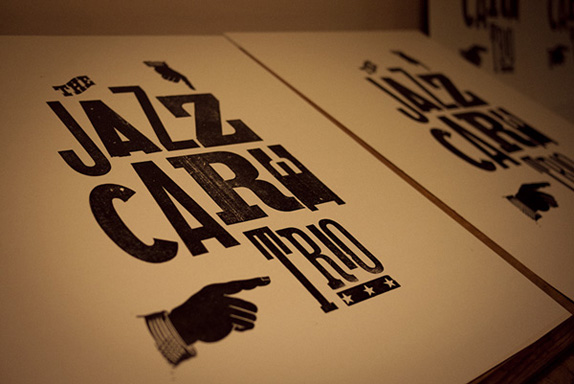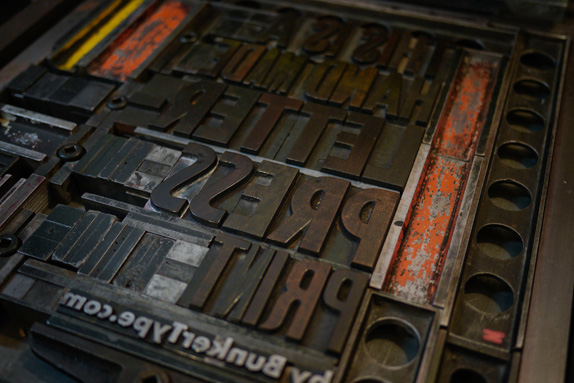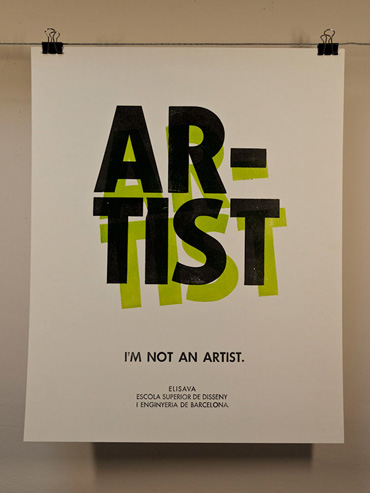
Hoy las computadoras nos ofrecen una suerte de depósitos virtuales en los que almacenamos gran cantidad de material sin ocupar espacio físico, y nos ofrece facilidad para acceder individualmente a cada uno de los archivos.En Bunker Type la realidad es diferente… Rodeado de Prensas, interlineas, filetes, tintas, y una gran colección de tipos móviles (150 familias de plomo en cuerpos relativamente grandes y 50 en madera) Jesús genera piezas gráficas artesanales colmadas de elegancia y sensibilidad.
«Voy recopilando de poco en poco… ¡pero sin pausa! Luego la mayoría de material no lo llego a usar… simplemente está ahí por si se necesita. Las técnicas que uso son muy básicas (…) son sencillas variaciones a partir del sistema de Gutenberg. Es todo muy primario en realidad, pero esos procesos pueden producir resultados muy bellos y sensibles.El mío es un taller parecido al que podría ser el taller de un pintor, con la única diferencia que en vez de usar pinceles yo uso letras antiguas.»
A pesar de las dificultades y limitaciones tecnológicas del sistema, que al momento de trabajar requieren una cuota extra de paciencia, Jesús encuentra en el proceso manual grandes ventajas muy importantes a la hora de manejar a la tipografía, como la precisión.
«Componer un texto en una tipografía Bodoni de 24 puntos puede llevarnos una hora. (…) Darnos cuenta que necesitamos un cuerpo menor un par de segundos. Desmontar el molde y el texto otra hora, y repetir el proceso con un cuerpo menor otra hora y media. Es decir, puedes necesitar casi toda una mañana para algo que en el ordenador conseguirías con un simple cmd+z» (Fragmento de entrevista para MDBY).
Jesús invita a reflexionar sobre el espacio de taller, los recursos, la clasificación, la experimentación, el autoaprendizaje y el estudio de las limitaciones. Pero lo más importante, a pensar su Bunker metafóricamente como un espacio que almacena valiosas herramientas y que fortalece con su trabajo diario la pasión por la tipografía.
Jesús Morentín es Diseñador Gráfico egresado de la Escuela d'Arts i Oficis Llotia, y tiene un postgrado de Infografía Mediática en la Universitat de Barcelona. Desde 1996 es docente en las Escuelas Superiores de Diseño ESDi de Sabadell, de Elisava y de Barcelona. En 2009 concretó/dio inicio a su proyecto personal, BunkerType.